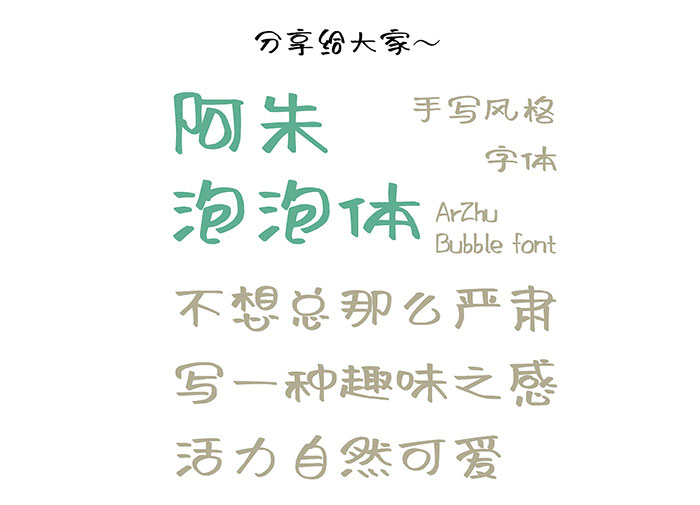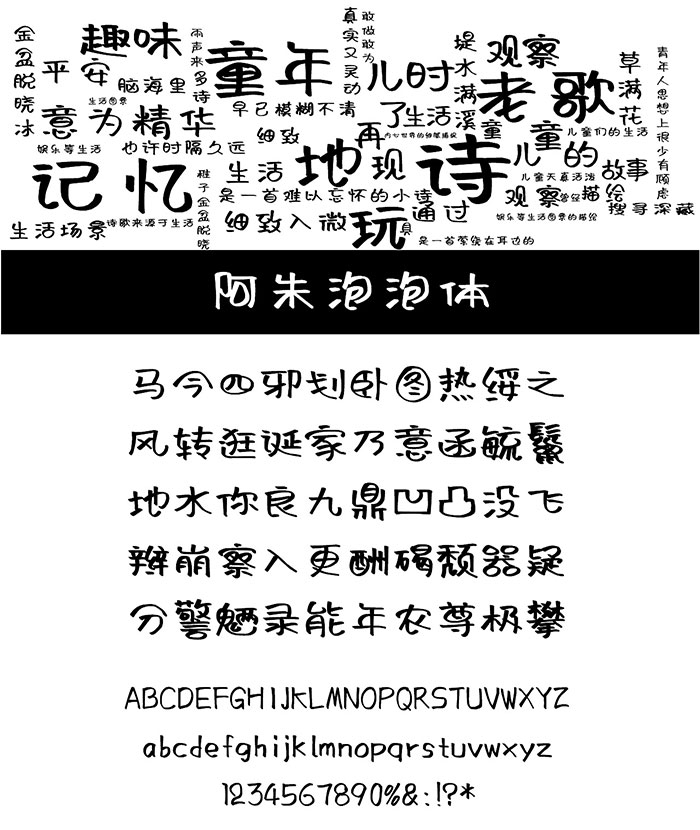
阿朱泡泡體,是一款字體書寫筆畫隨意放鬆,富於變化,充滿卡通趣味極富裝飾色彩,特別是口型偏旁由“泡泡”組成,使字體充滿青春活力風格鮮明,特點突出,能夠適用於藝術設計、包裝印刷、簽名設計、圖形設計等領域。
字數:本字體基於中華人民共和國GB2312-80字符集標準,共收容漢字6763個漢字和數百個符號。